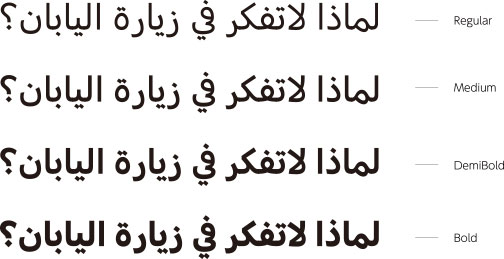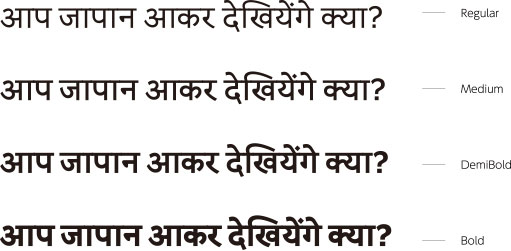
多言語(多言語フォント/多言語書体) を解説
日本語や英語に限らず、地域や文化により様々な言語がする。
そして、複数の言語が並存することを「多言語」という。
「多言語」は、一個の人間や、国家、社会、文書、コンピューター、Webサイト、ソフトウェアなどが複数個の言語に直面したり対応したりすることも意味している。
デジタルグローバル時代ともいえる現代において、ローカライズ対応などデジタルフォントにおいても多言語フォント(多言語書体)のニーズは大きく高まっている。
そこで、ラテン文字・ハングル・簡体字中国語・繁体字中国語など、主に日本語以外の世界各地の言語・文字「多言語(多言語フォント/多言語書体)」についてまとめてみた。
Adobe Illustratorで中東言語および南アジア言語を使用する場合の設定例:アラビア文字で「مرحبا(こんにちわ)」
アラビア文字で「مرحبا(こんにちわ)」と入力している。
ちなみにアラビア文字なので段落を右揃えにする。
通常通りやると文字が変になる。
そこで、環境設定メニューの「テキスト」を選択。
「インド言語のオプションを表示」にチェックを入れる。
「段落パネル」が切り替わり、「中東言語および南アジア言語単数行コンポーザー」「中東言語および南アジア言語段落コンポーザー」が選択できるようになるので、どちらをチェック。
作業終了後、「テキスト」を選択。「東アジア言語のオプションを表示」にチェックを入れる。
「日本語単数行コンポーザー」「日本語段落コンポーザー」が利用できるので、どちらかにチェックを入れると日本語など東アジア言語での文字組ができる。
Adobe Illustratorで中東言語および南アジア言語を使用する場合の設定例:デーヴァナーガリー(ヒンディー語)で「नमस्ते(こんにちわ)」
デーヴァナーガリー(ヒンディー語)で「नमस्ते(こんにちわ」と入力する場合も基本的な使用方法は変わらない。「中東言語および南アジア言語単数行コンポーザー」「中東言語および南アジア言語段落コンポーザー」が選択できるようになるので、どちらをチェック。ただし、デーヴァナーガリー(ヒンディー語)なので段落は左揃えとする。多言語入力で文字組が変になった場合、中東言語および南アジア言語コンポーザーを見てみると良い。
Adobe InDesignで中東言語および南アジア言語を使用する場合の設定例:アラビア文字で「مرحبا(こんにちわ)」およびデーヴァナーガリー(ヒンディー語)で「नमस्ते(こんにちわ)」
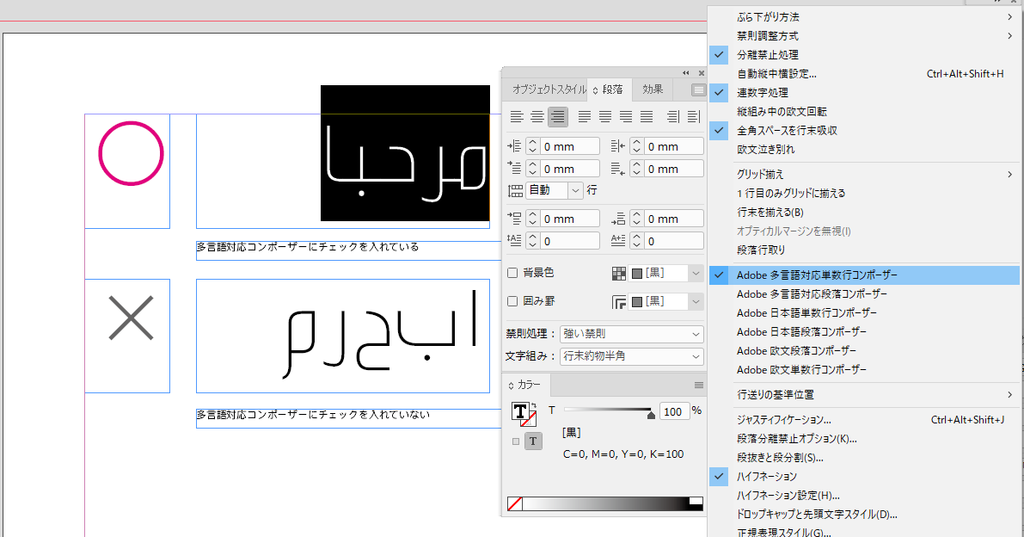
Adobe Illustratorより簡単に設定できる。単純に段落パネルを開いて「多言語対応コンポーザー」を選択するだけで正しく文字組みできる。
ラテン文字(欧文)
ラテン文字は世界で最も解読者人口が多い文字。
ハングル(韓国語)
ハングルは韓国語を表記するための表音文字。
主に朝鮮民族が使う言語で、朝鮮半島の韓国、北朝鮮、中華人民共和国延辺朝鮮族自治州で公用語として使用される。
簡体字(中国語)
簡体字は中華人民共和国で制定された従来の漢字を簡略化した字体。
中国大陸の他、シンガポールやマレーシアなどで使用されている。
繁体字(中国語)
繁体字は中国語簡体字と異なり系統的な簡略化を経ていない筆画が多い漢字の字体。
主に台湾や香港、マカオで使用されている。
ベトナム語(クオック・グー)
ベトナム語はベトナム社会主義共和国の総人口のおよそ87%を占めているキン族の母語で、ベトナムの公用語。ラテン文字を使用してベトナム語を表記する方法「クオック・グー」が用いられる。
タイ語
タイ語はタイ王国の公用語。文字の特徴はループがあることだが、このループは伝統的なタイ語書体には存在するが、ループのないモダンなデザインの書体もある。
ビルマ文字(ミャンマー語)
ビルマ文字は主にミャンマー連邦共和国の公用語としてビルマ語の表記に用いる文字。ビルマ文字は丸みを帯びたフォルムと弧を描いているような曲線で構成されているのが特徴。何故、丸いのかというと文字を書く時に紙の代わりに貝多羅葉を使用していたため貝多羅葉が裂けないように直線を使うのを避けたためという説がある。
ミャンマー語(ビルマ語)はミャンマー連邦共和国の公用語。